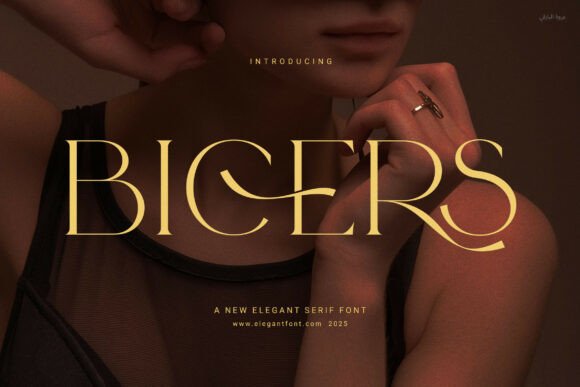
Bicers
適切なデザイン要素を見つけるのは難しい場合がありますが、Bicersは作品を即座に引き立てる優れたコレクションを提供します。
精密に作られたBicersは、クリーンなベクター、滑らかなタイポグラフィ、そして安心のための商用ライセンスを提供します。
POD(オンデマンド印刷)製品、結婚式の招待状、またはソーシャルメディアのグラフィックを作成している場合でも、Bicersは理想的です。